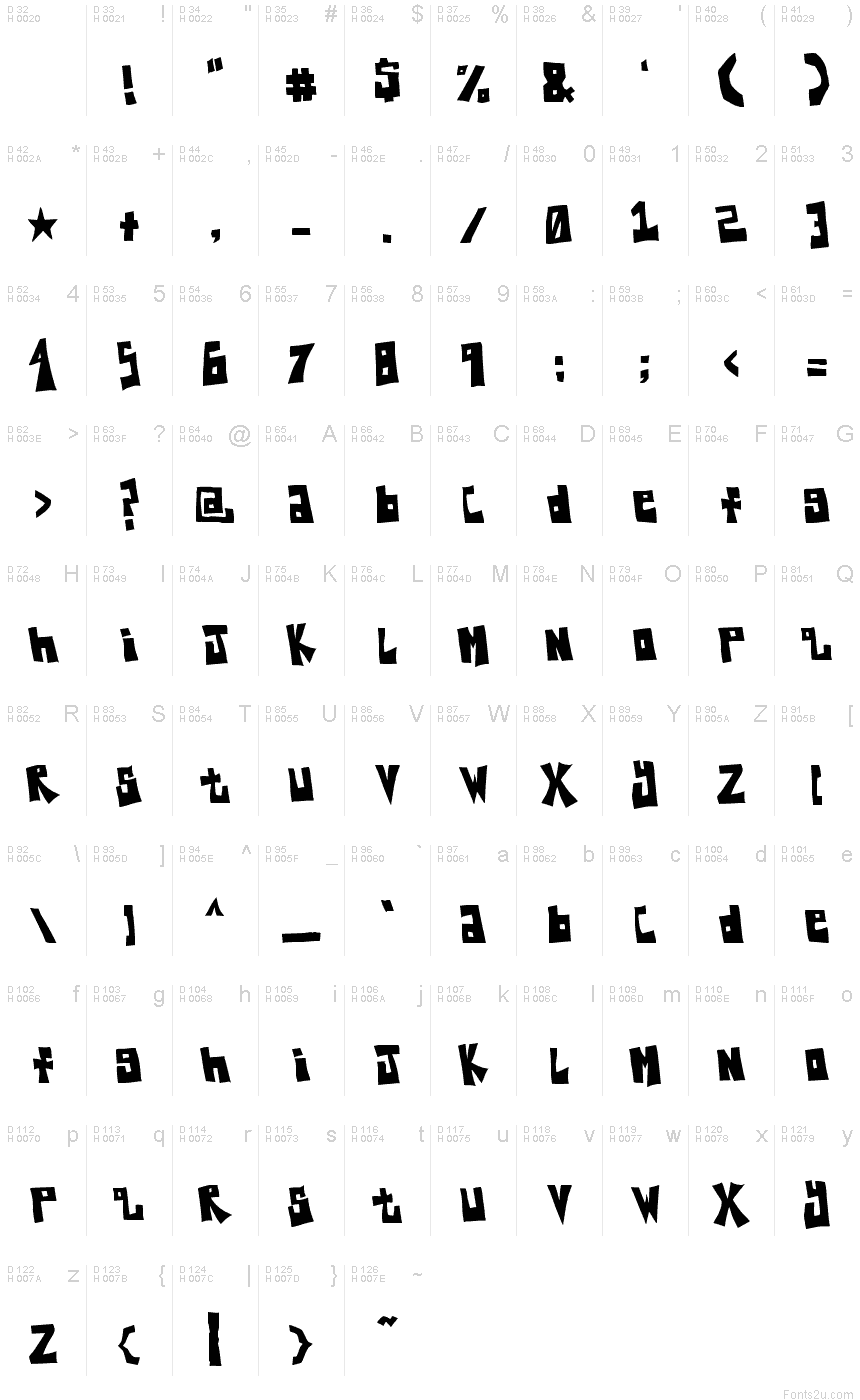
King of the Dragonflies od Jasona Skooga je bezplatné komiksové písmo s výrazným vzhledem, jako by bylo vystřižené z papíru. Vysoká, bloková písmena se mírně naklánějí a kolísají, takže působí jako ruční práce – připomínají hrubé, inkoustem otištěné dlaždice rozházené po stránce, ale přesto zůstávají čitelná. Tato kombinace těžkých černých tvarů a hravých nepravidelností dodává titulkům hlasitou, lehce chaotickou energii, kterou nelze přehlédnout.
S King of the Dragonflies dodáte plakátům, zinům, obálkám dětských knih, herním titulkům, náhledům videí na YouTube nebo návrhům samolepek syrový DIY nádech. Rozestupy jsou těsné a úderné, takže písmo nejlépe vynikne ve velké velikosti. Pro menší texty kombinujte tento bezplatný font s čistým geometrickým bezpatkovým písmem, aby vše zůstalo přehledné a vyvážené.